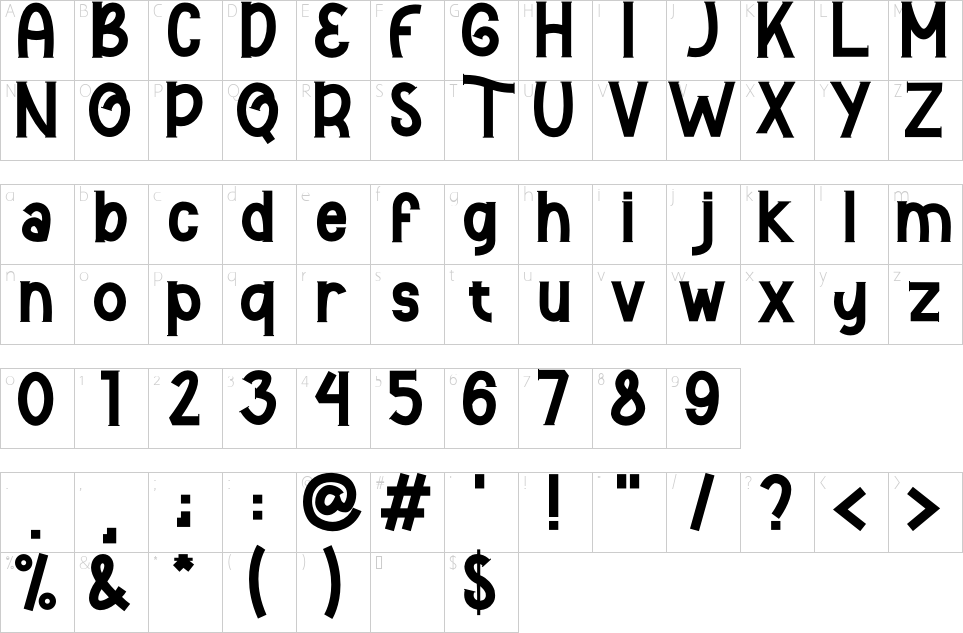
A fonte “Baby Angel Font” é uma delicada e suave seleção de letras feita especificamente para pais e mães que desejam transmitir um carinho especial através de seus textos. Desenvolvida pela StringLabs, esta fonte leva um toque de gentileza e delicadeza que se destaca em qualquer tipo de layout gráfico, especialmente em designs para bebês e crianças. Com uma aparência aconchegante e suave, ela é perfeita para criações de bebês, gráficos de aniversários infantis e até mesmo para anotações cuidadosamente elaboradas. Download gratuita para os usuários do Windows e Mac, esta fonte vem embalada com todo o amor e cuidado, tornando-a uma escolha perfeita para qualquer projeto gráfico que deseje expressar carinho e ternura. A cada download, você contribui para uma fonte que ajuda a transmitir amor e suavidade através do design.